「明朝体(デフォルト)への問い」 岡田一祐×舟山貴士
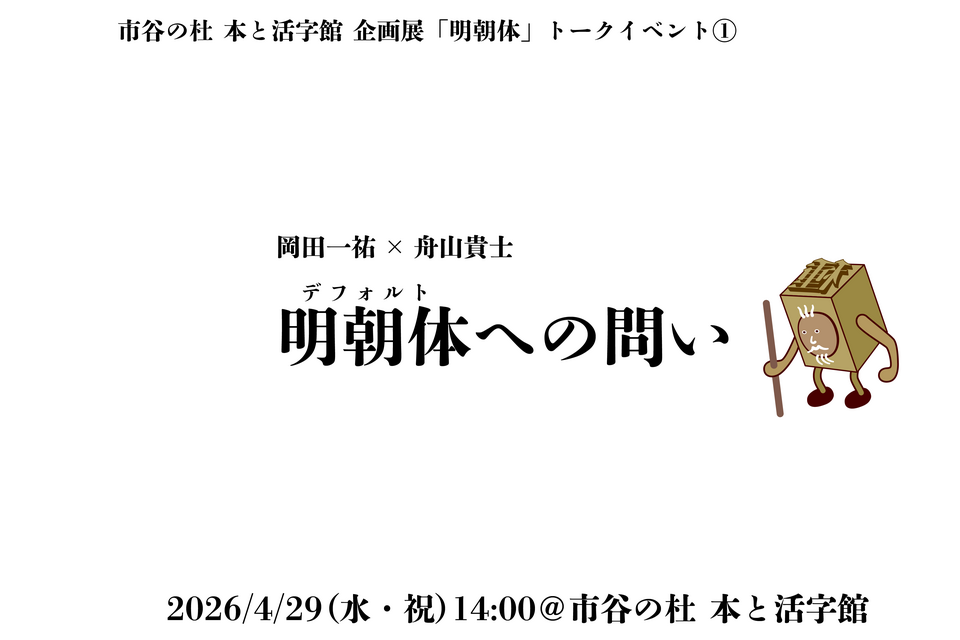
市谷の杜 本と活字館では、4/29(水)に、企画展「明朝体」関連イベントとして、「明朝体(デフォルト)への問い」と題し、慶應義塾大学准教授の岡田一祐さんとデザイナーの舟山貴士さんに学術的な視点から、明朝体についてお話しいただきます。
市谷の杜 本と活字館では、企画展「明朝体」関連イベントとして、より明朝体に詳しくなり、身近に感じられるトークイベントを開催いたします。
ふだん当たり前のように目にし、とくべつ意識することは少ない「明朝体」という存在。150年以上にわたる日本での長い歴史の中で、様々な人の手によって磨かれ、活躍してきた明朝体は、デフォルト――日本人にとって標準の書体といえるのではないでしょうか。
4/29(土)は、「明朝体(デフォルト)への問い」と題し、本展監修の慶應義塾大学准教授の岡田一祐さんとデザイナーの舟山貴士さんにお話しいただきます。メディアが変化していく中で、明朝体がどのような役割を果たしてきたのか、また、どのように作られてきたのか、研究者とデザイナーの視点それぞれの角度からお話いただきます。
明朝体をより深く理解できるトークイベント、ぜひご参加ください!